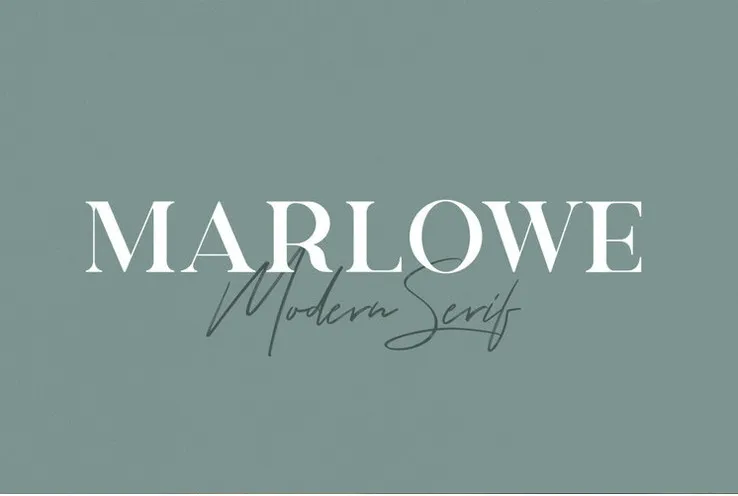
Marlowe Font – Fonte Grátis
Marlowe Font
A fonte Marlowe é uma elegante serif font moderna criada pela Font Forestry para quem busca personalidade no seu design visual. Cada letra foi cuidadosamente moldada, garantindo que sua mensagem seja imprevisível e chamativa. Marlowe faz mais do que apenas estabelecer um único tipo de texto: é uma escolha ideal tanto para conjuntos com fontes script ou sans serif, quanto para textos isolados. Esta fonte perfeita combina maravilhosamente com variadas aplicações gráficas, desde embalagens de produtos e capas de revistas até cartões de visita, selos logotípicos e anúncios de casamento. Sua versatilidade torna Marlowe uma fonte ideal para expressar sua identidade visual de maneira única em múltiplas aplicações gráficas. Como qualquer bom designer de fontes, Font Forestry criou algo que vai além da aparência clássica das serif fonts e oferece um design moderno e diferenciado.